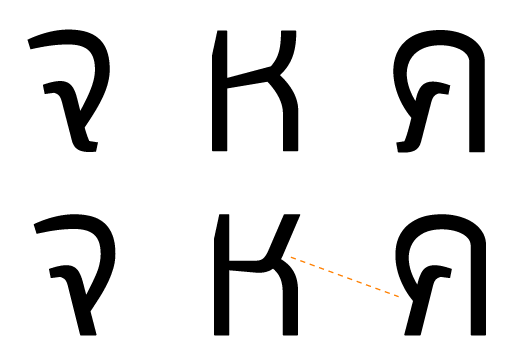
โว้วววว เฟี้ยวขึ้นสามเท่า
อยากเห็น ฎ กับ ฏ
ฎ ฏ ฐ
โอ้ว
โอย เข็ดฟัน โคตรเปรี้ยวเลย
ยอดมากครับ
ตัดทอนขั้นสุดท้ายครับ
เอาไอ้ติ่งๆ ออกไป / ห หีบใหม่ โดยเอาโครงสร้างมาจาก ค ควาย
ไม่มีเวลาทำให้เสร็จสักที ภาษาอังกฤษก็ยังไม่ได้เริ่มเลย
ไว้มาดู typesetting กันครับ
สวยกระแทกมาก
ชอบ จอจาน
เป็นฟอนต์ที่ใช้เวลาทำนานมากครับ
เพราะดองนาน
จานโม่ดองงาน
นิดหน่อยๆ เจ้าชื่นชมเกินไปแล้ว
นึก text ไม่ออก
ผมขอค้านครับท่านประธาน !!!
ข้อความของจานโม่ที่ใช้ทดลอง Text มีความชี้นำมากเกินไปครับ
(ตูจะอ้วกว่างั้นเถอะ)
ชี้นำอะไร้
อย่าจีบกันครับ
พอเอามาวางทั้งชุดดันรู้สึกว่า ตระกูล ก มันชิงดีชิงเด่นชาวบ้านเกินไปแฮะครับ
ทั้งที่พอวางเดี่ยวๆ มันเปรี้ยวมากแท้ๆ